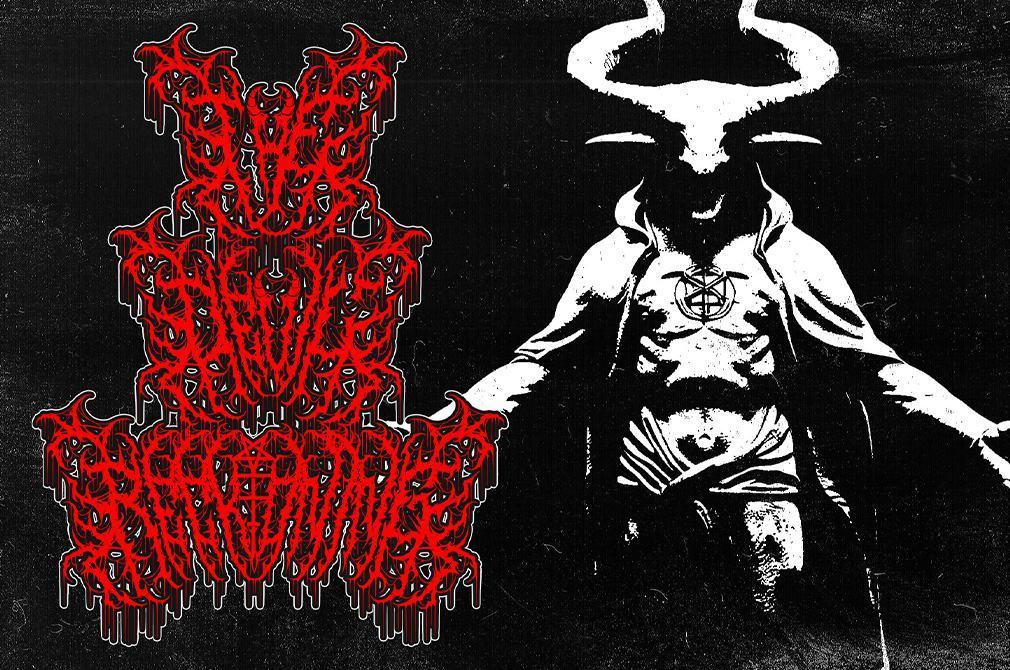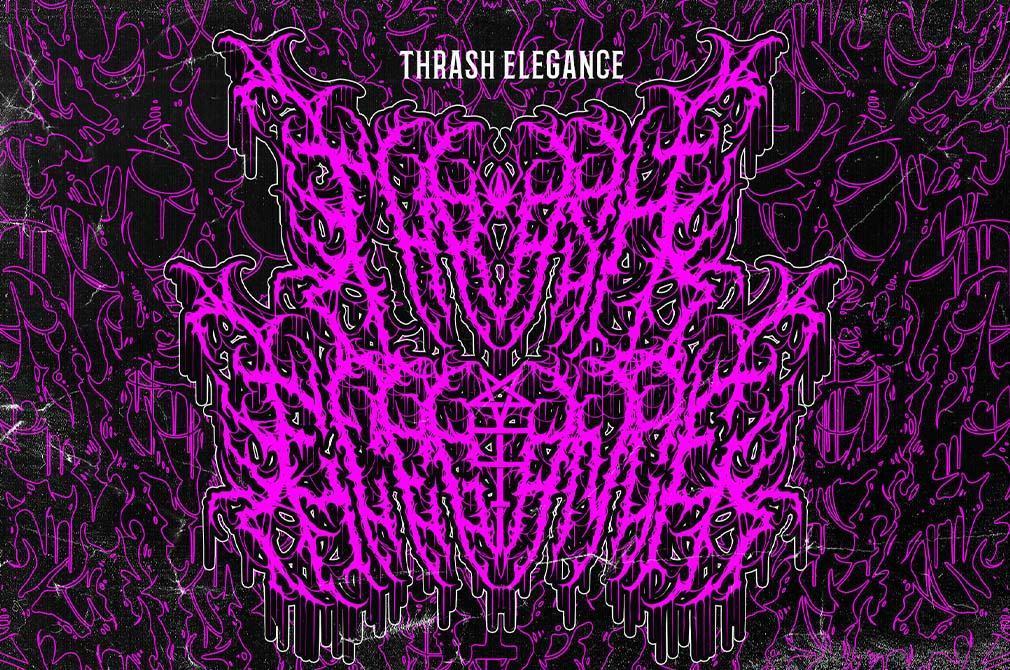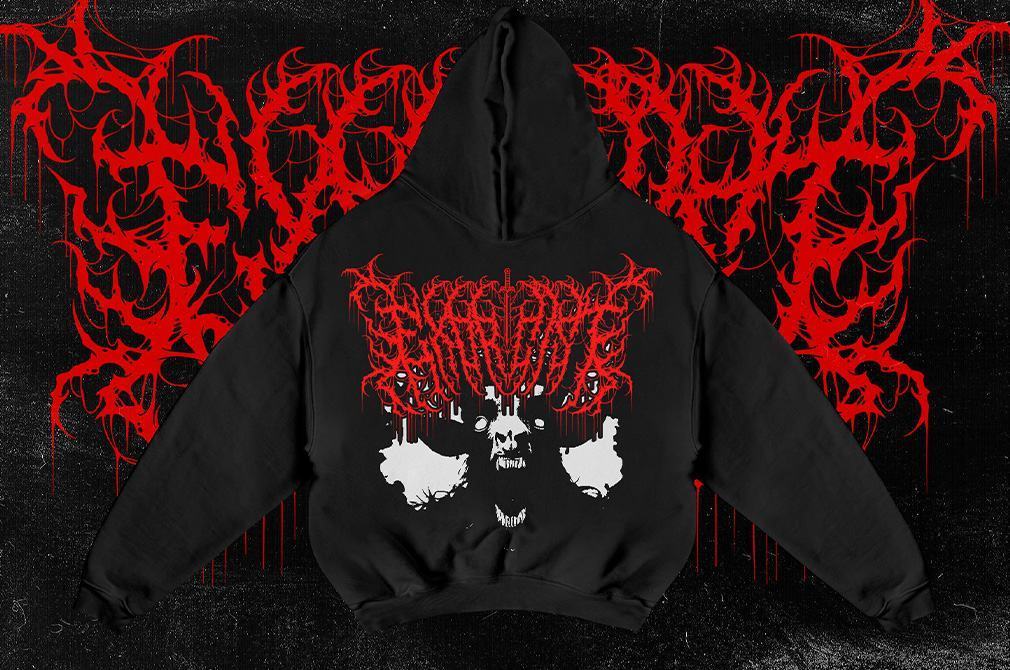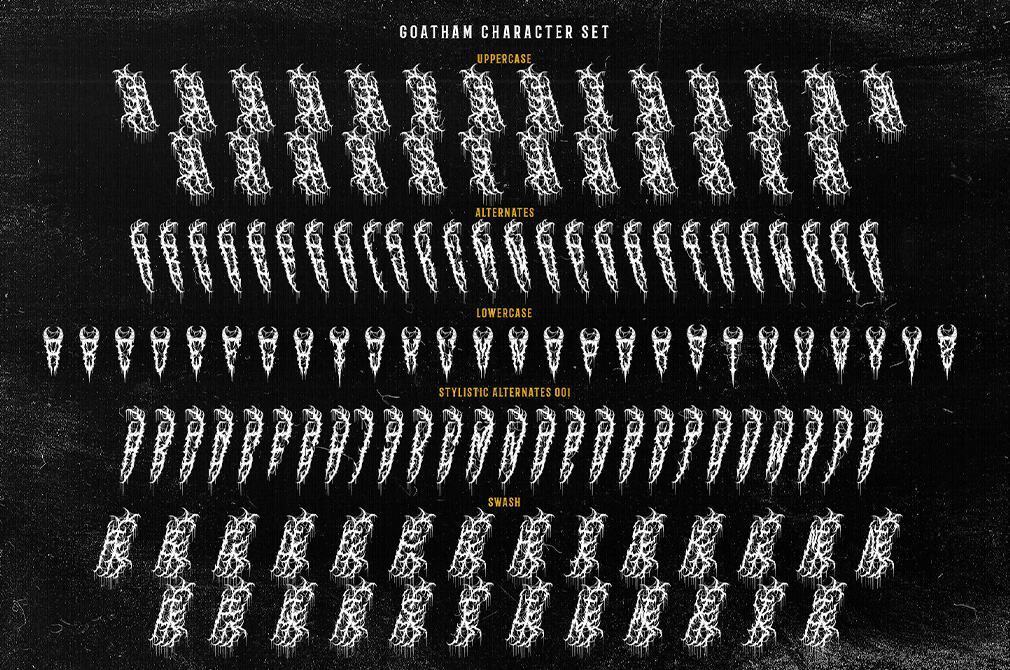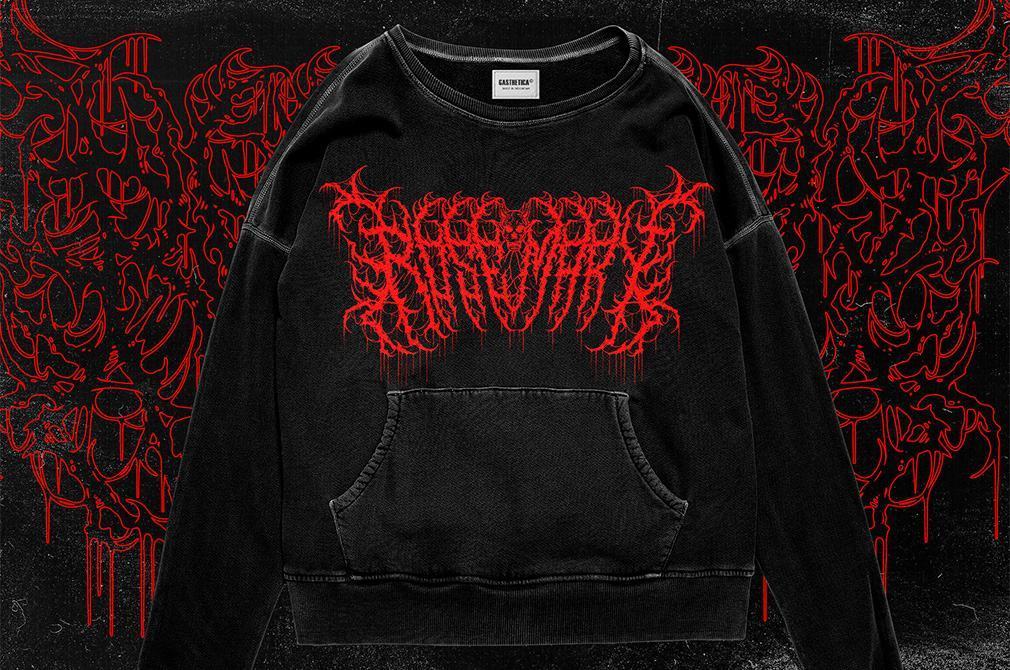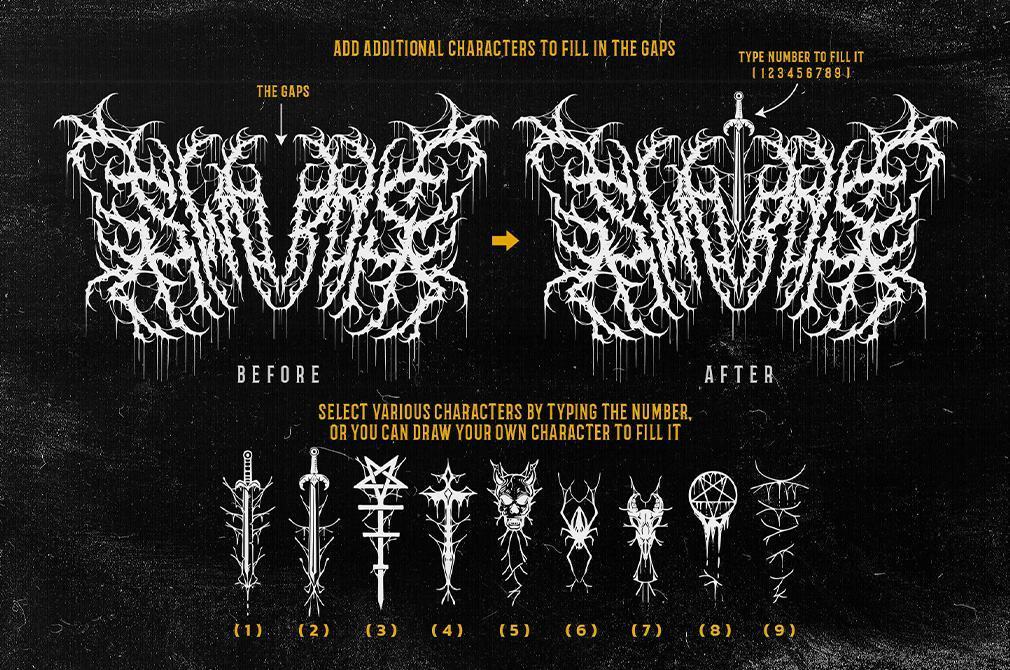
Trước đây, chưa ai trong chúng ta từng nghĩ Gotham City là một nơi ảm đạm ĐẾN NHƯ VẬY. Tuy nhiên, chỉ một font chữ kim loại đơn lẻ đã khiến chúng ta phải diễn giải lại câu chuyện về Batman và Joker, biến nó thành một bản hùng ca của sự đen tối.
GOTHAM kết hợp hình ảnh kim loại truyền thống với độ chi tiết và chất lượng của các font chữ hiện đại. Đây là một phát hiện hiếm có dành cho các nhà thiết kế làm logo ban nhạc; bìa album và hàng hóa, chẳng hạn như áo thun, vòng đeo tay và phím đàn guitar. Sự độc đáo của nó thể hiện ở thiết kế ký tự chính xác và một bộ ký tự mở rộng. Font chữ được mã hóa PUA và có các chữ hoa, nét lượn và các lựa chọn thay thế gần như không giới hạn.